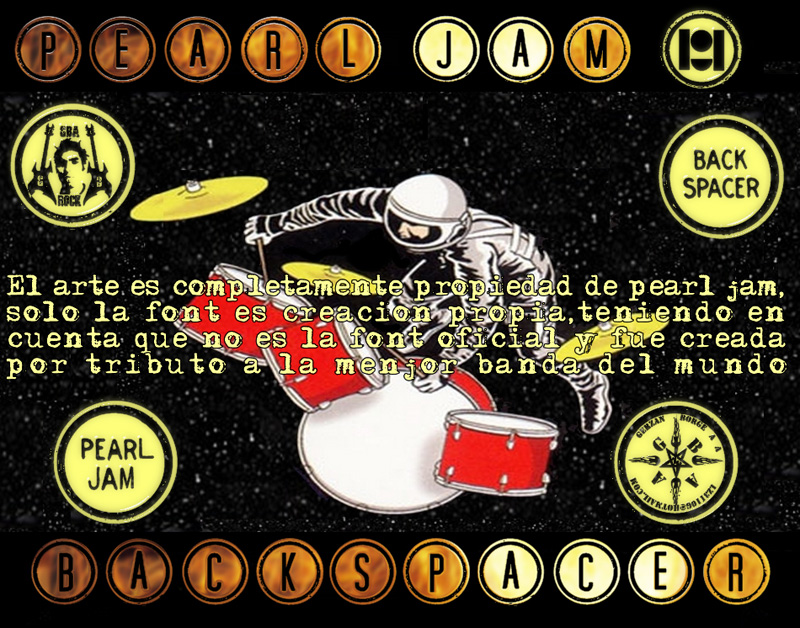
Note of the authorEsta no es la fuente oficial que se utilizo para el backspacer del disco de pearl jam!, es una fuente alternativa!
This is not the official source that was used for the backspacer of the album of pearl jam !, it is an alternative source!